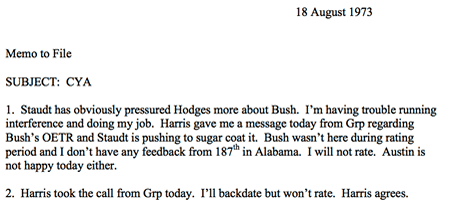
Avez-vous vu le film Truth, avec Cate Blanchett et Robert Redford, au sujet
de la controverse sur le service militaire de Georges Bush ? Personnellement,
j’ai bien aimé le film, qui n’a pourtant pas eu de très bonnes critiques. Je
l’ai aimé justement parce que ce n’est pas une "success story" de l’histoire
de la presse, mais plutôt un genre de fiasco. Je l’ai aussi aimé parce que
Mais la typo y joue aussi un grand rôle, puisqu’un des enjeux principaux est
de savoir si un texte dactylographié en 1973 peut ressembler de très très
près à ce que MS Word produit avec les réglages par défaut en 2004. Voilà un
bon sujet pour notre ami Jacques André, à qui j’ai immédiatement pensé en
voyant le film (mais je n’avais aucun souvenir de cette polémique de 2004...)
Comme souvent, le film est assez allusif sur ces sujets, sans aller au fond,
mais avec de bons moments quand même sur l’existence ou non d’un digramme th
supérieur, accessible sur les machines à écrire, et sur les caractères
proportionnels ou non des machines des années 1970.
Heureusement, Wikipedia nous en dit beaucoup plus (le contraire m’eût
étonné). C’est là :
Un GIF animé superpose deux compositions : celle prétendument datée de 1973
et le Times New Roman composé par MW Word en 2004. Déjà une remarque : la
fonte n’est (à mon avis) manifestement pas la même en 1973, pour ce qui
concerne le dessin des caractères. Ça me semble assez clair malgré
l’imprécision de l’image. (Je trouve que ce point n’est pas assez souligné.)
Mais en dehors de cette remarque perso, l’article Wikipédia revient sur des
tas de choses savoureuses. Notamment le nombre d’unités sur lesquelles la
largeur des caractères des machines d’époque comme l’IBM Selectric Composer
était étalonnée (9 unités), bien moins finement que ce qu’un traitement de
texte sait faire. On parle également des apostrophes et quotes, courbes ou
non.
On regrette quand même que les commentaires généraux semblent avoir pris le
pas sur l’expérience. Personne ne semble avoir exhumé une IBM Selectric en
état de marche, avec les différentes familles de caractères disponibles en
1973, pour ensuite dactylographier le texte et voir ce que ça donne. Est-ce
que vraiment personne n’était en mesure de faire cela ? Il est vrai que CBS
ayant rapidement fait marche arrière et présenté des excuses, plus personne
n’était payé pour faire ça...
On peut aussi se reporter à l’article Wikipédia sur les IBM Selectric, dont
bien sûr les "IBM à boule".
Les différents arguments semblent malgré tout faire penser à un "fake",
d’autant que tous les autres documents d’époque produits par les mêmes
services de l’armée étaient dactylographiés avec une chasse fixe.